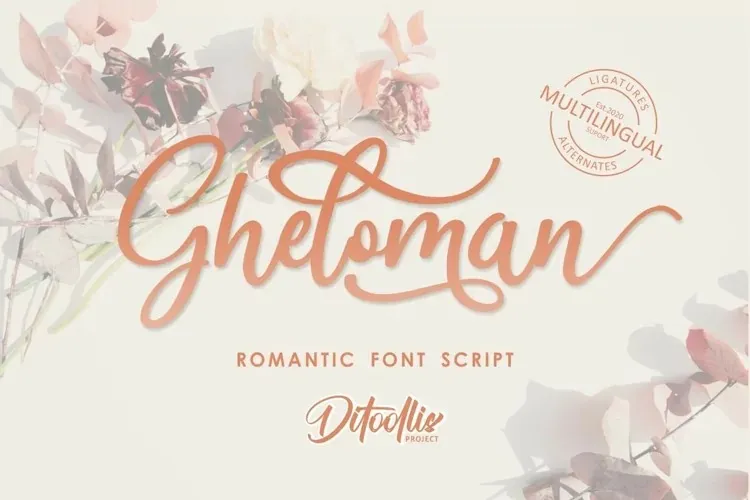
Gheloman Font – Fonte Grátis
Gheloman Font
A Gheloman Font é uma elegante fonte script feita por Ditoollis Project que traz uma aparência suave e delicada perfeita para designers criativos. Suas linhas curvadas e acentos naturais fazem dela uma escolha ideal para qualquer aplicação onde há um ar de sofisticação e charme, desde as cards de negócios até os logos e capas de livros. Esta fonte é perfeita para quem procura um toque suave em design de revistas e cartazes ou para adicionar um toque especial a invitations personalizadas. Com sua aparência arredondada e harmoniosa, a Gheloman Font se destaca como uma excelente opção para criações que valorizam o cuidado com detalhes. O designer 99designs trouxe esta fonte do seu armário de recursos creativos para oferecer a um público vasto, criando uma solução versátil e sofisticada para as necessidades de design moderno. Seja você um profissional desejando dar um toque final personalizado a suas criações ou um artista em busca de novas ideias, Gheloman Font pode ser o elemento que transforma seu trabalho no próximo grande hit de design.